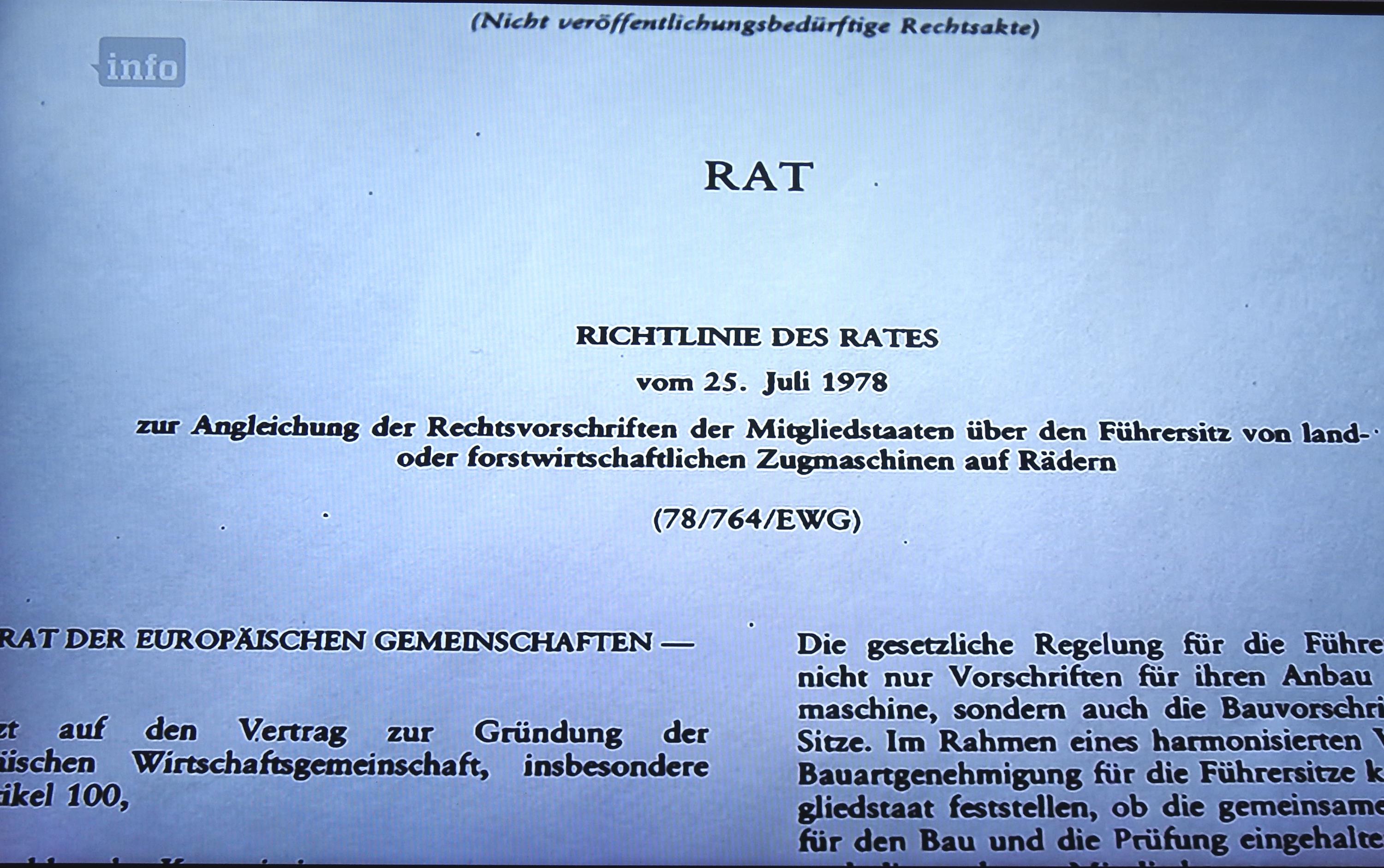
Schriftart Bundesgesetzblatt 1978 und/oder Hausschrift Ministerrat der EWG
In einer ZDFinfo-Doku über sieben Fehler der EU, die ich am 06.09.2017 gesehen haben, wurde auch dieses Gesezesblat eingefügt. Es ging um die Size von Traktoren, doch der Inhalt ist belanglos.
Mich interessiert die verwendete Schriftart. Eine Recherche ergab, dass diese Richtlinie entweder direk vom Rat veröffentlich oder - wahrscheinlicher - in einem deutschen Gesetzesblatt erschien. Solche Richtlinien sollen wohl im Bundesgesetzblatt erschienen sein.
Das gerade f und das Recht breite ö in der Kursiven oben, weisen auf Sabon hin … der Rest dann evtl auch?!
Heute verwendet das Amtsblatt der Europäischen Union die Albertina (EUAlbertina – Hausschrift der EU), das nur am Rande.